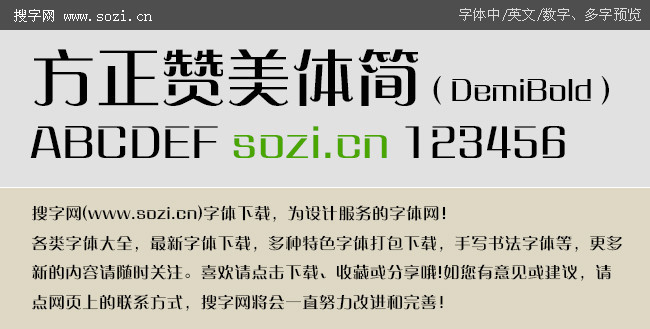
方正贊美體簡(jiǎn)DemiBold
搜字網(wǎng)提供一款方正贊美體簡(jiǎn)DemiBold中文藝術(shù)字體下載,方正贊美體字體設(shè)計(jì)很特別,橫劃和直劃都不相連,形成一缺口,這就是這款字的特式,加上橫細(xì)豎粗強(qiáng)烈對(duì)比亦有宋體的風(fēng)格,因此贊美體好適合女士們的品牌,如時(shí)裝,內(nèi)衣褲,化妝品,減肥,纖體等廣告宣傳和包裝設(shè)計(jì)。